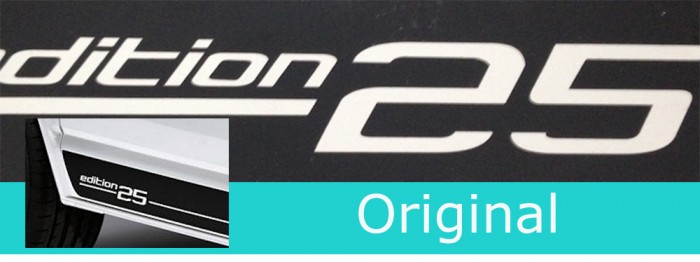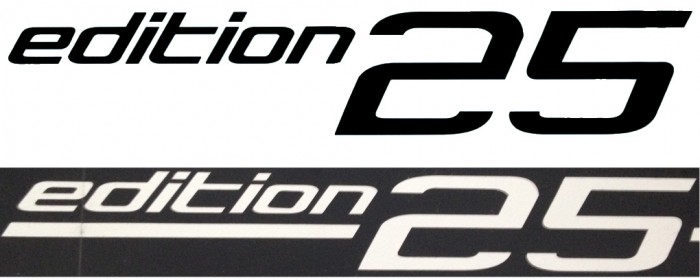
VW T5 Edition 25 Schriftart gesucht
ich suche schon etwas länger nach der exakten Schriftart vom VW T5 edition 25.
WhatTheFont hilft mir nicht weiter, die Typo "Otomo" kommt der Sache schon sehr sehr nahe, aber das kleine "e" und die Zahlen passen z.B nicht.
Ich hoffe Ihr könnt meiner Suche ein Ende bereiten.